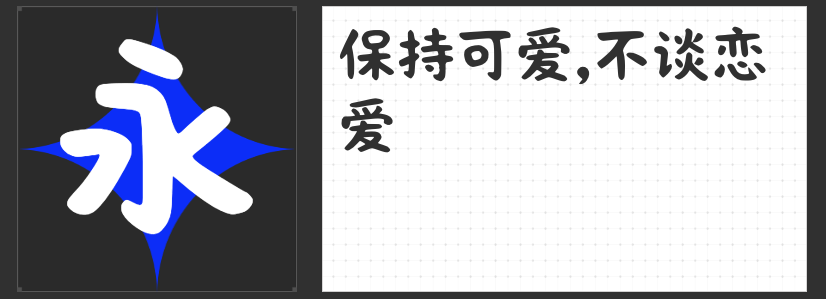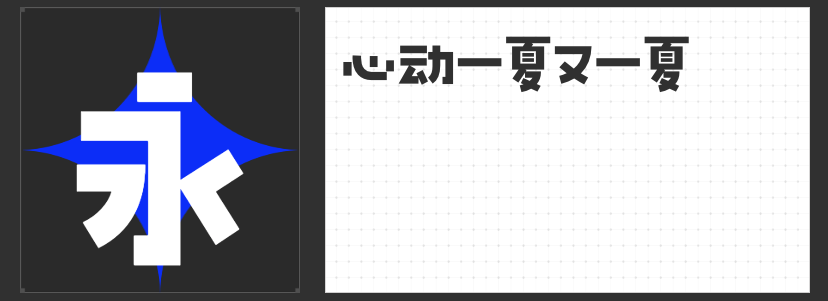
萌动视界:四款治愈系可爱字体唤醒设计童心
在追求情感共鸣的视觉设计中,可爱字体如同棉花糖般柔软的力量,瞬间融化观者的心防。以下四款免费商用字体,以其各具特色的萌系表达,为设计注入天真烂漫的治愈能量。
一、字恋狂澄空 鸣风
这款字体以松散的字型架构和略低的重心,模拟孩童学书时的稚拙韵律。笔画粗细均匀如蜡笔涂鸦,折角处平直的切角处理消解了锐气,而笔画的"断开"设计更添轻快的呼吸感。当"口"字被压缩成扁圆造型,"走之底"却舒展如飘带,这种反差萌在组合排版时形成跃动的节奏感,适合儿童绘本与文创周边设计。
二、励字小星星简
拙朴的线条与均匀的布白构成这款字体的视觉骨骼,每个笔画都像是用蜡笔反复描摹后的痕迹。设计师刻意放大的偏旁部首占比,让"雨字头"化作云朵,"四点底"变成星星,在保持高辨识度的同时,将童真趣味转化为现代装饰语言。无论是二次元游戏界面还是奶茶包装,都能精准传递温暖治愈的情绪。
三、MyFont郑明瑾卡通简
圆润到几乎看不见棱角的字形轮廓,让每个字符都仿佛带着婴儿肥。柔和的转角处理与自然弧线构成"永"字八法的现代变奏,竖弯钩处夸张的弧度像上扬的嘴角,横折处饱满的弧度似鼓起的腮帮。这种拟人化设计使其天然适配儿童书籍与母婴用品,字里行间流淌着令人愉悦的亲和力。
四、大萌卡通体
"大"字舒展如拥抱的双臂,"萌"字草字头化作摇曳的花朵,这款字体用夸张的纵横比例重构汉字美学。圆润的笔画边缘泛着糖霜般的光泽,部分结构突破常规框架的"溢出"设计,让文字仿佛从童话书里跳脱出来的精灵。适用于卡通IP开发与主题乐园视觉,在数字屏幕与纸质媒介间架起童趣的桥梁。
这四款字体如同设计师的"情绪糖果",在严肃的商业设计中植入温柔的情感锚点。它们或模拟孩童学书的稚拙,或将自然形态融入笔画,以不同维度的可爱表达,为品牌注入亲和力,为画面增添故事感。在追求差异化的设计竞技场,不妨用这些萌系字体搭建通往观众内心的彩虹桥。